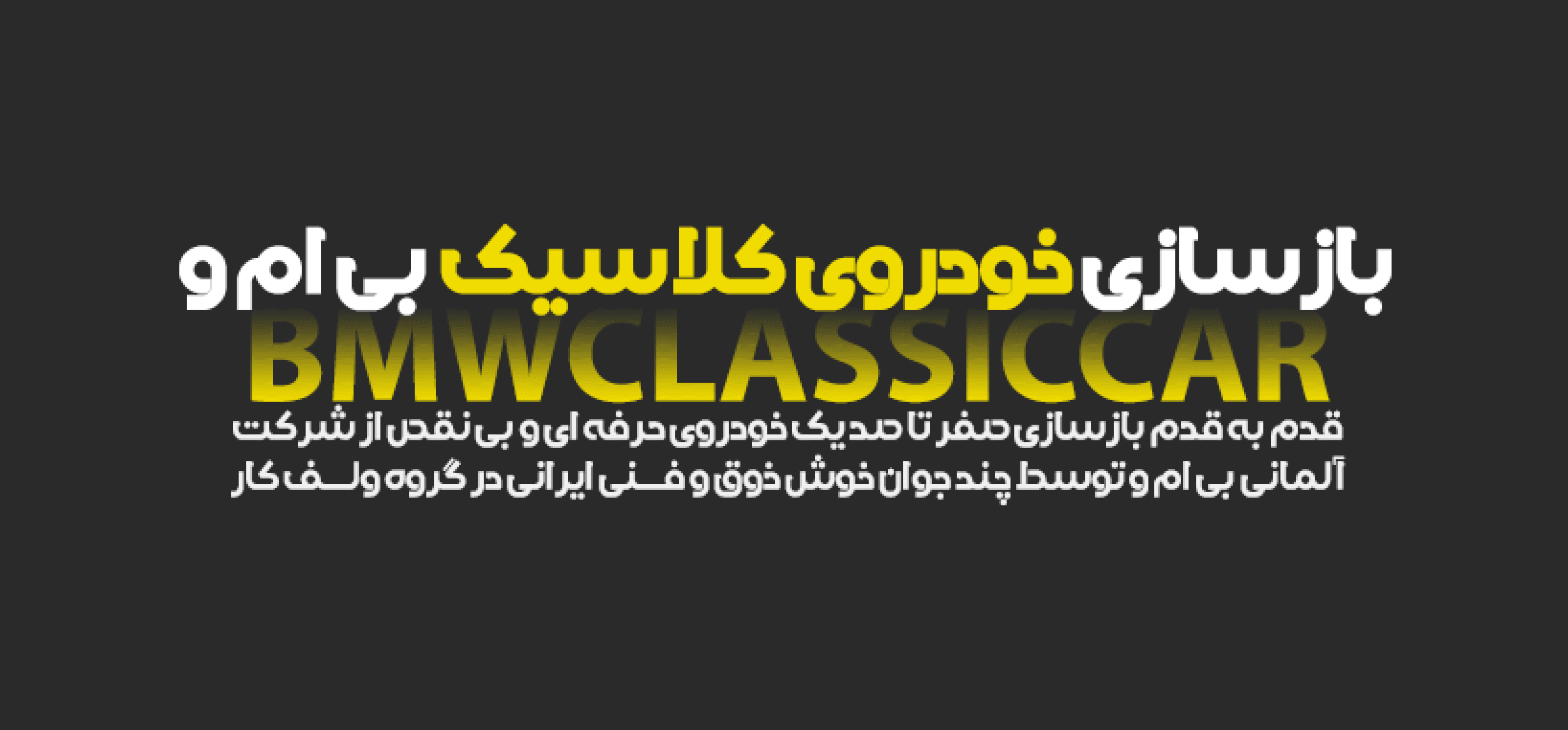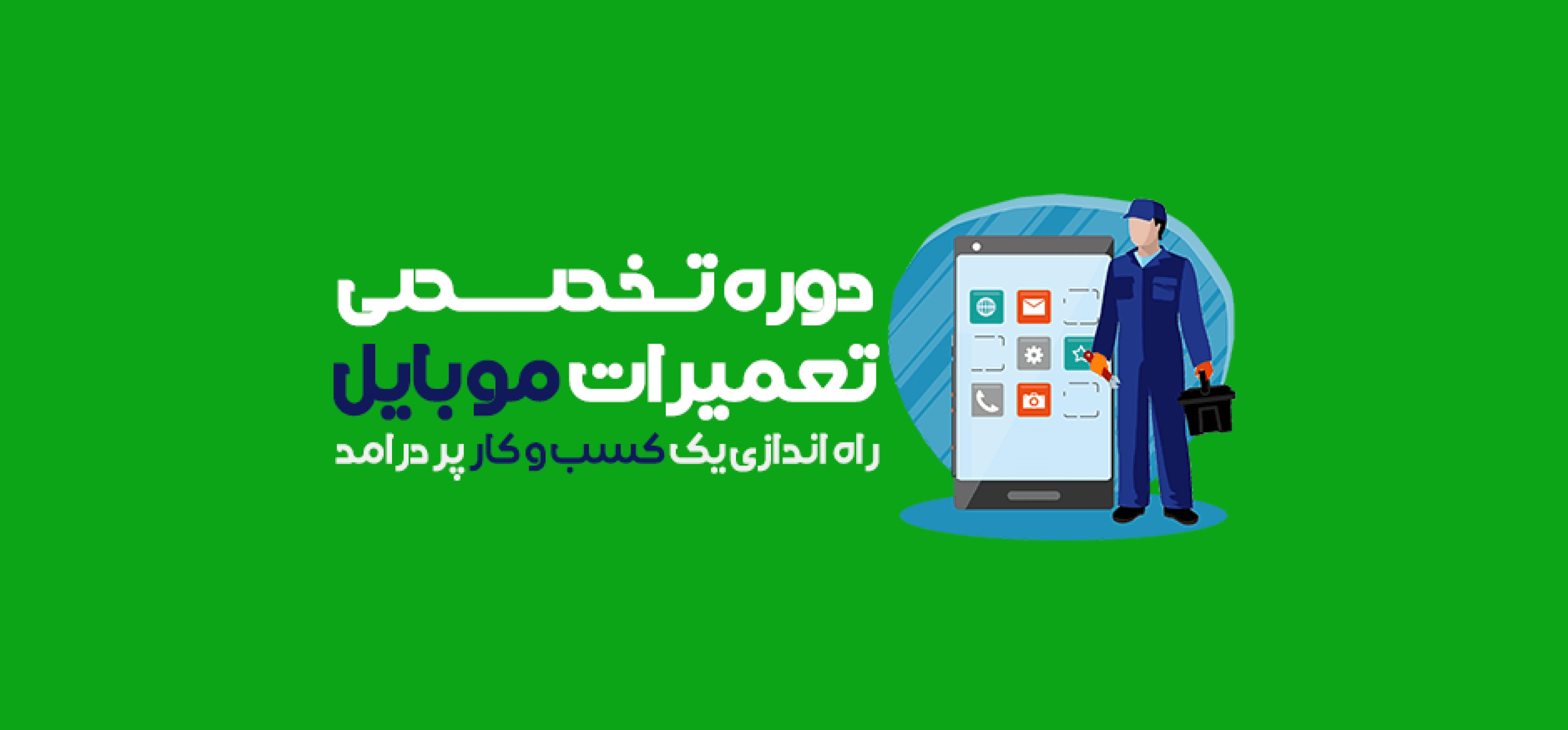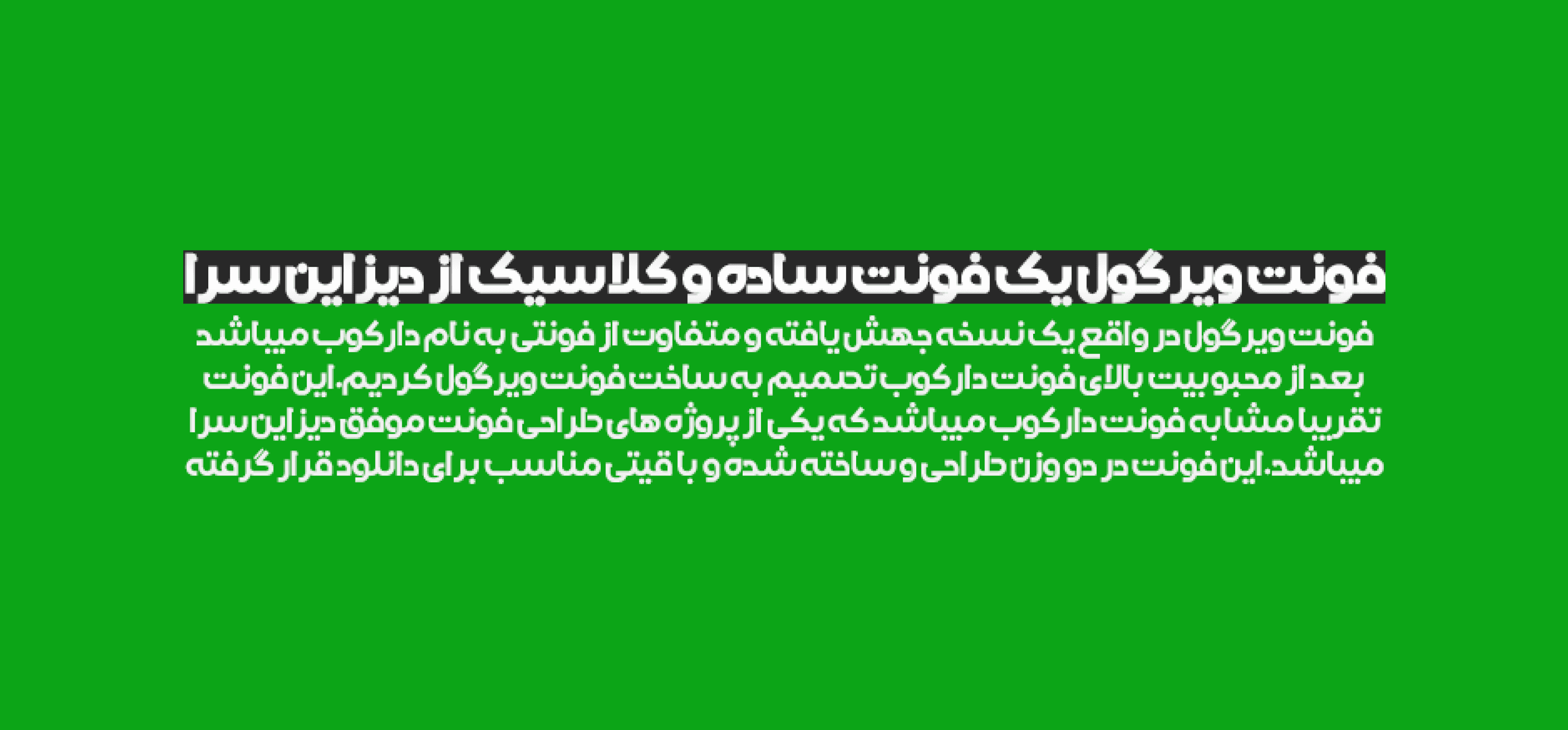
خط "ویرگول" هو منتج فارسي جديد من موقع "ديزاینسرا"، ويُعد نسخة مُعدّلة ومحسّنة من خط "داركوب"، أحد أكثر الخطوط شعبية على المنصة والذي حظي بإقبال واسع. وقد تم نشره تحت اسم مختلف لأسباب معينة.
يتميّز هذا الخط الجميل والاحترافي بجودة عالية جدًا، وهو مصمّم بوزنين مختلفين.
خط "ویرگول" مناسب لمختلف أنواع التصاميم الجرافيكية، وخاصة في إنتاج محتوى منصات التواصل مثل إنستاگرام، حيث يمنح المظهر الجذاب والعصري.